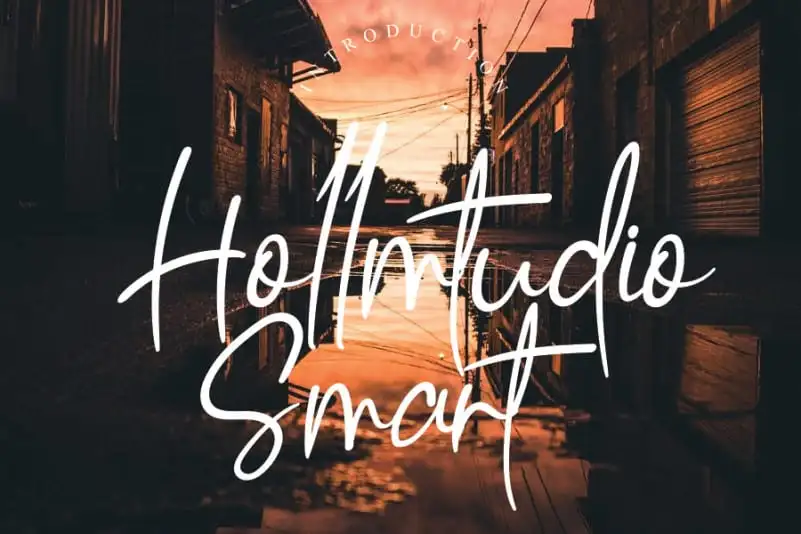
Hollmtudio Handwritten Font – Download Grátis
A Hollmtudio Handwritten Font é uma fonte escrita a mão com um toque descontraído e distintivo que traz vida e autenticidade às criações digitais. Perfeita para quem busca adicionar um toque romântico e único em seus trabalhos, esta fonte é um complemento ideal para os mais variados projetos, como convites de casamento elegantes, arte para cartões de visita memoráveis ou postagens atraentes nas redes sociais. Sua versatilidade permite que você explore inúmeras possibilidades criativas sem comprometer o seu estilo único. Doe uma pitada de personalização ao design digital com a Hollmtudio Handwritten Font e transforme suas ideias em realidade, seja para um projeto de arte pessoal ou profissional.